Font cổ trang Việt hóa ngày càng được nhiều designer lựa chọn nhờ khả năng tạo nên vẻ đẹp hoài cổ và ấn tượng trong thiết kế. Tuy nhiên, không phải ai cũng hiểu rõ từng loại font và cách ứng dụng phù hợp.
Trong bài viết này, In Viva sẽ tổng hợp các loại font chữ cổ trang việt hóa phổ biến cùng đặc điểm và ứng dụng cụ thể để dễ dàng lựa chọn cho từng nhu cầu thiết kế.
Font cổ trang việt hóa là gì?
Font chữ cổ trang việt hóa là nhóm phông chữ được thiết kế theo phong cách thư pháp, cổ điển Á Đông hoặc Trung Hoa xưa, sau đó được Việt hóa để hỗ trợ đầy đủ dấu tiếng Việt. Những font này thường mang nét bay bổng, uốn lượn và giàu tính nghệ thuật, giúp tái hiện không khí cổ xưa trong thiết kế.
Khác với các font hiện đại, font cổ trang tập trung vào yếu tố cảm xúc và thẩm mỹ, thường được dùng để tạo chiều sâu văn hóa và phong cách riêng cho ấn phẩm.
Đặc điểm nổi bật của font cổ trang việt hóa
Font việt hóa cổ trang mang nhiều nét đặc trưng riêng, giúp tạo nên phong cách hoài cổ và đậm chất nghệ thuật trong thiết kế:
- Phong cách thư pháp đặc trưng: Nét chữ mô phỏng bút lông với độ đậm nhạt linh hoạt, tạo cảm giác mềm mại, uyển chuyển và giàu tính nghệ thuật.
- Đậm chất cổ điển Á Đông: Hình dáng chữ lấy cảm hứng từ chữ Hán và văn hóa xưa, mang lại cảm giác trang trọng, hoài niệm và có chiều sâu văn hóa.
- Nét chữ đa dạng: Có thể là kiểu bay bổng, uốn lượn hoặc dạng gãy gọn, dứt khoát, phù hợp nhiều phong cách thiết kế khác nhau.
- Hỗ trợ tiếng Việt đầy đủ: Các font đã được việt hóa hoàn chỉnh, hiển thị đúng dấu và ký tự tiếng Việt, giúp sử dụng ổn định trong thiết kế.
- Tính thẩm mỹ cao: Dễ tạo điểm nhấn cho tiêu đề, logo hoặc typography nghệ thuật mà không cần quá nhiều hiệu ứng bổ trợ.
- Ứng dụng linh hoạt: Phù hợp cho poster, bìa sách, thiệp mời, banner hoặc các ấn phẩm mang phong cách cổ trang, retro.
- Tạo cảm xúc mạnh: Giúp thiết kế mang lại cảm giác hoài cổ, tinh tế và khác biệt so với các font hiện đại.
Nhờ những đặc điểm này, font cổ trang việt hóa thường được sử dụng trong các thiết kế cần yếu tố cảm xúc và tính thẩm mỹ cao.
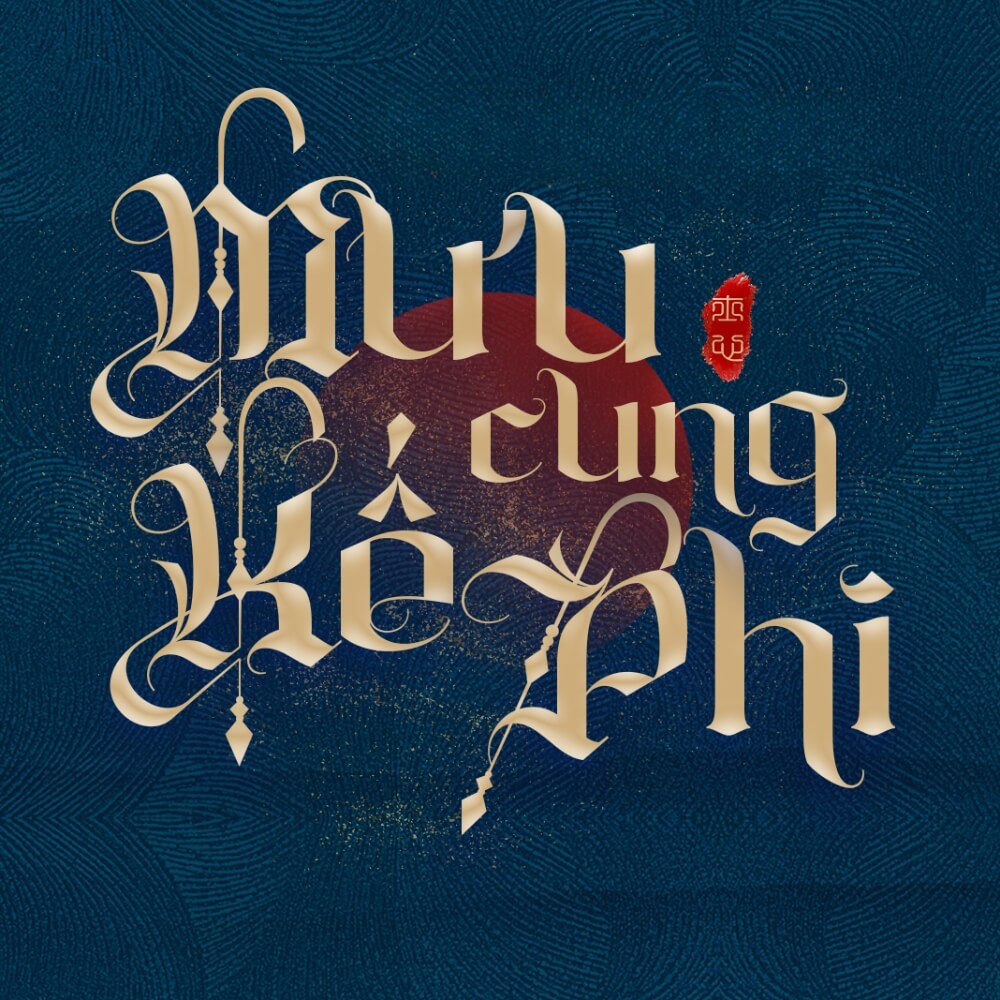
Font cổ trang việt hóa không chỉ đa dạng về kiểu dáng mà còn mang nhiều phong cách khác nhau, từ mềm mại bay bổng đến mạnh mẽ cổ điển. Việc hiểu rõ từng loại font sẽ giúp bạn lựa chọn đúng phong cách phù hợp với thiết kế và mục đích sử dụng.
Loại font |
Đặc điểm |
Ứng dụng |
| Font thư pháp | Nét chữ bay bổng, uốn lượn như viết tay |
Thiệp mời, câu đối, poster nghệ thuật |
| Font kiếm hiệp | Nét mạnh mẽ, cá tính, dứt khoát |
Poster phim cổ trang, game, banner |
Font triện cổ |
Nét vuông, dày, giống con dấu cổ | Logo, ấn phẩm mang tính truyền thống |
| Font calligraphy cổ điển | Mềm mại nhưng rõ ràng, dễ đọc |
Logo, typography, thiết kế cao cấp |
Ứng dụng của font chữ việt hoá cổ trang
Ứng dụng font cổ trang việt hóa trong thiết kế
- Thiết kế poster phim, truyện hoặc game cổ trang.
- Làm logo thương hiệu mang phong cách truyền thống.
- Thiết kế bìa sách, truyện kiếm hiệp, fantasy.
- Typography nghệ thuật, quote, artwork.
- Thiết kế banner sự kiện văn hóa, lễ hội.
Không chỉ dùng trên màn hình, font chữ cổ trang việt hóa còn được ứng dụng trong nhiều sản phẩm in ấn:
- In logo trên hộp quà mang phong cách cổ điển.
- In thiệp mời, thiệp cưới concept truyền thống.
- In poster, standee cho sự kiện văn hóa.
- Khắc laser trên gỗ, bút, quà tặng thủ công.
- In bao bì sản phẩm handmade hoặc sản phẩm truyền thống.
Khi sử dụng đúng chất liệu và kỹ thuật in, font cổ trang giúp sản phẩm trở nên ấn tượng và có giá trị thẩm mỹ cao hơn.
Lưu ý khi sử dụng font cổ trang trong thiết kế
Đây là nhóm font đẹp nhưng khá “kén” cách dùng, nên bạn cần lưu ý:
- Không dùng cho đoạn văn dài vì khó đọc.
- Nên dùng cho tiêu đề, logo hoặc điểm nhấn chính.
- Kết hợp với font đơn giản để cân bằng bố cục.
- Kiểm tra dấu tiếng Việt trước khi sử dụng.
- Convert outline trước khi in để tránh lỗi font.
Việc sử dụng đúng cách sẽ giúp font phát huy tối đa hiệu quả thẩm mỹ.
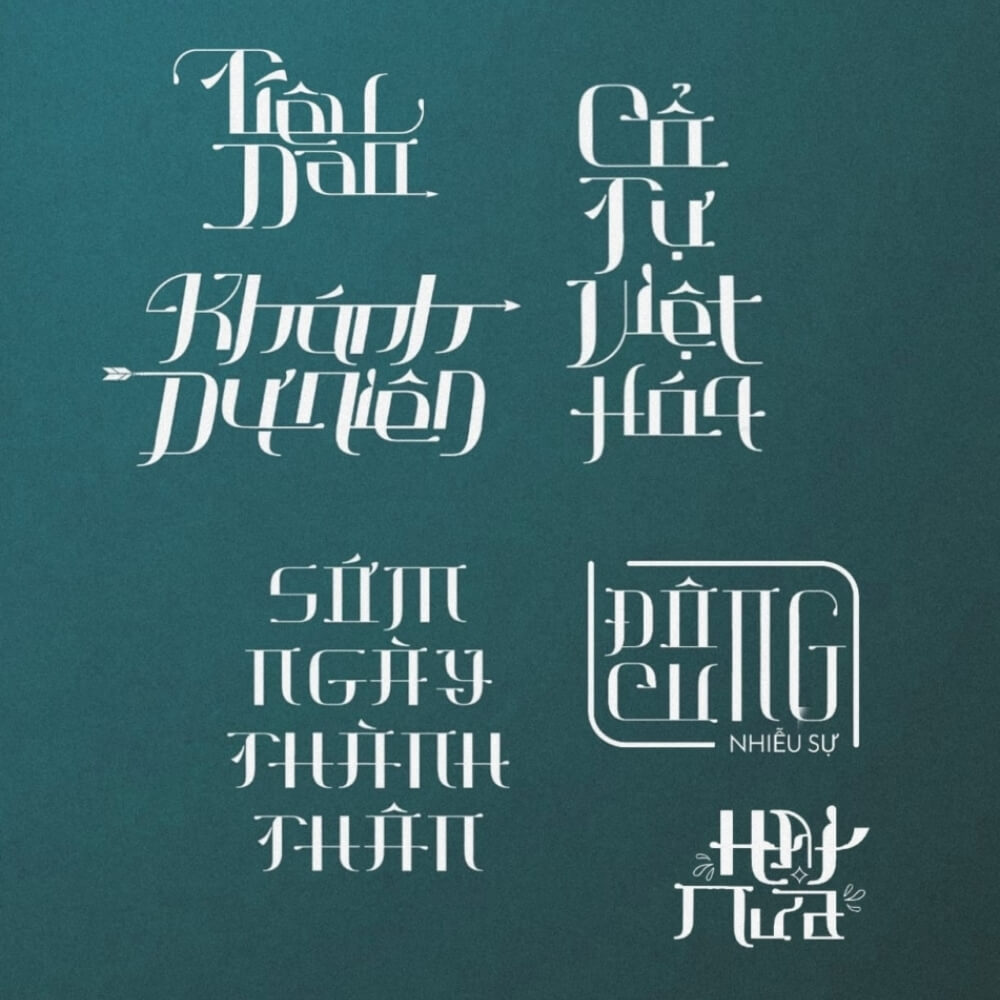
Font cổ trang Việt hóa không chỉ giúp tái hiện vẻ đẹp hoài cổ mà còn mang lại chiều sâu thẩm mỹ và cảm xúc cho từng thiết kế. Khi lựa chọn đúng kiểu chữ phù hợp, bạn có thể dễ dàng tạo nên những ấn phẩm ấn tượng, đậm chất nghệ thuật và khác biệt.